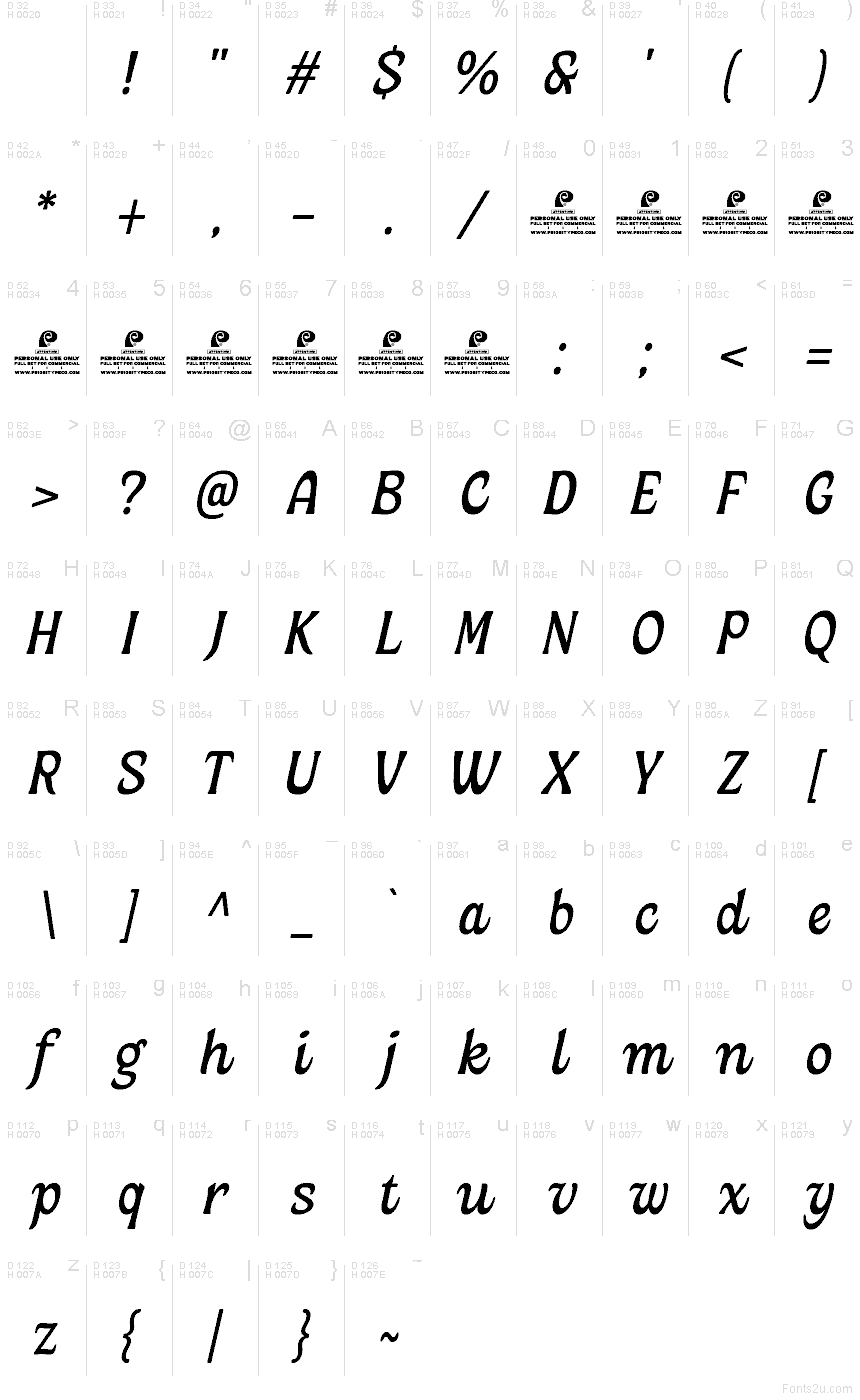
Ombre Nouveau, de Prioritype Co., es una tipografía display cursiva de estilo Art Nouveau, de descarga gratuita, con trazos largos y fluidos que evocan la suavidad de los carteles clásicos. Sus letras capturan la esencia del cambio de siglo, combinando curvas amplias y uniones afiladas para que el resultado sea ornamental sin resultar cargante.
Funciona de maravilla en la identidad visual de cafeterías, packaging de perfumería o velas, portadas de libros, carteles de eventos y titulares de revistas donde un toque teatral marca la diferencia. Al ser gratuita, también es perfecta para tarjetas de título, bocetos de logotipos y frases cortas, ya que su ritmo inclinado y sus remates elegantes aportan una clara presencia vintage incluso a pocas palabras.
Ombre Nouveau DEMO